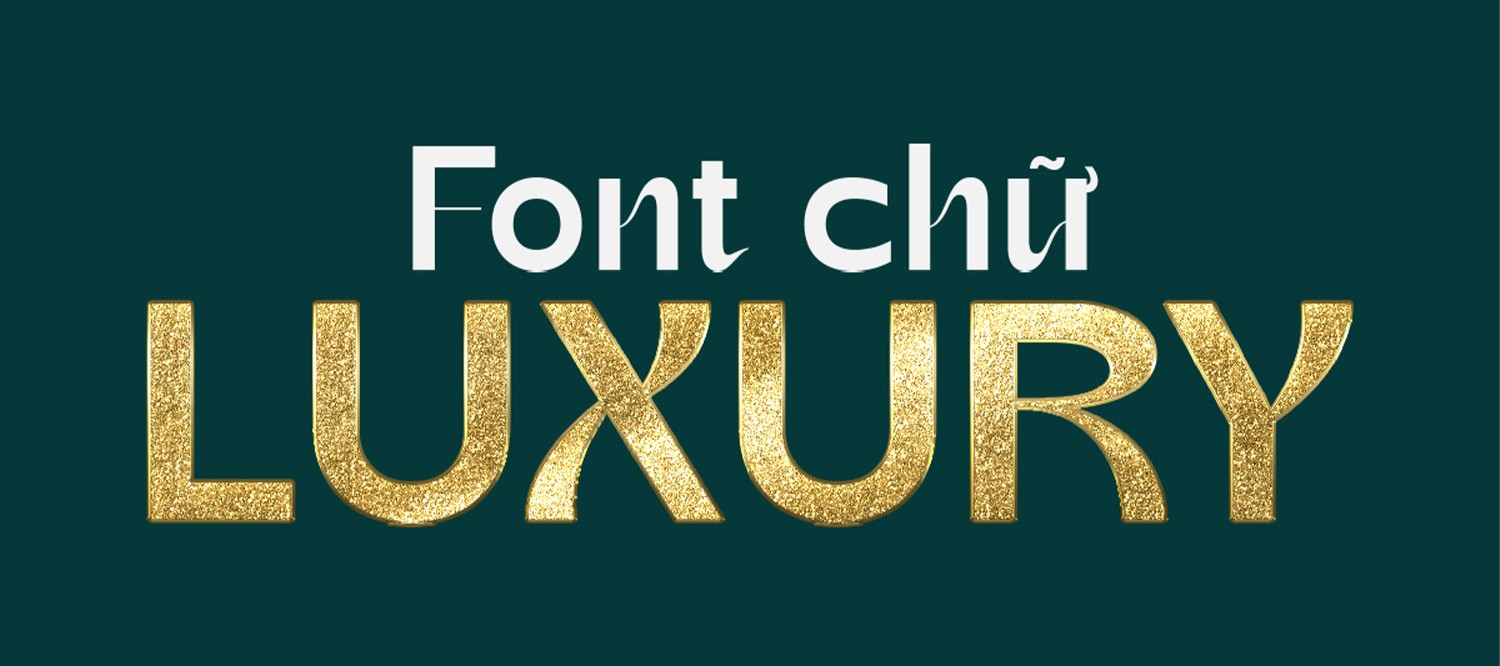
![[Tải Xuống] TOP 15 Font Chữ Luxury Cho Thiết Kế Trở Lên Sang Trọng](https://cdn.s99.vn/blog/fontluxury2.jpg)
Font chữ là yếu tố cực kỳ quan trọng trong thiết kế đồ họa, đặc biệt là với các dự án mang tính chất cao cấp và đẳng cấp.Font chữ luxury, hay còn gọi là font chữ sang trọng, là những kiểu chữ được thiết kế với mục đích tạo ra cảm giác cao cấp, đẳng cấp và tinh tế. Chúng thường được sử dụng trong các thiết kế đòi hỏi sự sang trọng như logo thương hiệu cao cấp, thiệp cưới, ấn phẩm quảng cáo cao cấp, và nhiều hơn nữa.
Font chữ luxury mang đến cảm giác sang trọng, tinh tế và chuyên nghiệp. Đặc trưng bởi đường nét thanh mảnh, tỷ lệ cân đối và chi tiết được thiết kế tỉ mỉ, font luxury thường là serif cổ điển hoặc sans serif hiện đại. Khoảng cách chữ rộng rãi tạo sự thoáng đãng và thanh lịch. Một số ký tự được cách điệu nhẹ nhàng để tạo điểm nhấn riêng biệt. Font luxury phù hợp cho thiết kế logo, bao bì mỹ phẩm, thiệp mời hay thương hiệu cao cấp, giúp nâng tầm hình ảnh và thu hút sự chú ý một cách tinh tế.
Dưới đây là các font chữ luxury sang trọng đã được Việt hóa, phù hợp cho thiết kế thương hiệu cao cấp, thiệp mời, bao bì sản phẩm và nhiều ấn phẩm đòi hỏi sự tinh tế, đẳng cấp. Những font này giúp bạn tạo điểm nhấn ấn tượng và chuyên nghiệp.
Font chữ TH Luxury 7 mang phong cách sang trọng và đậm chất luxury, với các đường nét thanh lịch, mềm mại nhưng vẫn dứt khoát. Thiết kế chữ cái cân đối, phần chân và đỉnh chữ được xử lý tinh tế tạo cảm giác cao cấp, cổ điển. Font phù hợp cho các thiết kế thương hiệu thời trang, mỹ phẩm, bao bì sản phẩm hay thiệp cưới cao cấp. TH Luxury 7 đã được Việt hóa, giúp người dùng dễ dàng ứng dụng trong các ấn phẩm tiếng Việt mà vẫn giữ nguyên vẻ đẹp đẳng cấp vốn có.
Font chữ TH Luxury 5 gây ấn tượng với kiểu dáng hiện đại, thanh thoát và mang đậm tính thẩm mỹ. Các chi tiết uốn cong nhẹ nhàng ở phần chân và đuôi chữ tạo nên cảm giác mềm mại, rất phù hợp cho các thiết kế trong lĩnh vực spa, làm đẹp hay chăm sóc sức khỏe. Phông chữ này mang hơi hướng tối giản nhưng vẫn đủ tinh tế để truyền tải thông điệp về sự thư giãn và cao cấp. TH Luxury 5 là lựa chọn lý tưởng cho thương hiệu cần sự trang nhã và chuyên nghiệp.
Font chữ TH Runsling thuộc nhóm Serif với thiết kế đầy nghệ thuật và sự phá cách trong từng chi tiết. Các nét gạch chân được xử lý uyển chuyển, tạo độ chuyển động nhẹ nhàng, mang đến cảm giác vừa cổ điển vừa hiện đại. Phần đầu chữ được kéo dài hoặc cách điệu một cách tinh tế, giúp font trở nên nổi bật trong các dự án branding, bìa sách hay thiết kế cao cấp. Với phong cách độc đáo và cá tính, TH Runsling là lựa chọn lý tưởng cho những ai yêu thích font Serif mang đậm tính biểu cảm và sáng tạo.
Font chữ TH Vadola gây ấn tượng với kiểu dáng nét mảnh, tinh tế và mang đậm tinh thần luxury hiện đại. Từng ký tự được thiết kế cao ráo, thanh thoát, tạo cảm giác nhẹ nhàng nhưng đầy cuốn hút. Font đặc biệt phù hợp cho các dự án trong lĩnh vực thời trang, làm đẹp hay thiết kế thương hiệu cao cấp, nơi cần sự chỉn chu và sang trọng. Với TH Vadola, mỗi dòng chữ trở nên thanh lịch và đậm chất nghệ thuật, góp phần nâng tầm hình ảnh chuyên nghiệp cho thiết kế.
Font chữ TH Glowen trong ảnh mang hơi thở hiện đại với dáng chữ Serif thanh thoát, được Việt hóa hoàn chỉnh để sử dụng mượt mà trong thiết kế tiếng Việt. Các chi tiết được chăm chút với đường nét mảnh – dày xen kẽ, tạo nên sự tương phản độc đáo, giúp văn bản trở nên nổi bật và thu hút. Font phù hợp với các dự án thiết kế thương hiệu cao cấp, bìa sách, poster nghệ thuật hoặc thời trang. TH Glowen là lựa chọn hoàn hảo cho những ai đang tìm kiếm một kiểu chữ Việt hóa mang phong cách sang trọng, sáng tạo và đầy cá tính.
Font chữ TH Waking sở hữu vẻ đẹp cuốn hút với phong cách thiết kế mang hơi hướng luxury, phù hợp với các thương hiệu trong ngành làm đẹp. Các nét chữ được uốn cong nhẹ nhàng, kết hợp cùng độ dày mảnh linh hoạt tạo cảm giác mềm mại nhưng vẫn giữ được sự sang trọng. Font đã được Việt hóa đầy đủ, hỗ trợ tiếng Việt mượt mà mà không làm mất đi tính thẩm mỹ nguyên bản. Đây là sự lựa chọn lý tưởng để thiết kế logo, bao bì mỹ phẩm hay các ấn phẩm quảng bá cao cấp.
Font chữ TH Ginger sở hữu tỷ lệ chữ cân đối cùng đường nét dứt khoát, mang lại cảm giác mạnh mẽ nhưng không kém phần thanh lịch. Với lối thiết kế mang tính biểu tượng và hiện đại, font này dễ dàng tạo nên dấu ấn cao cấp cho các dự án về thời trang, tạp chí hay nhận diện thương hiệu. Sự sắc sảo trong từng chi tiết giúp TH Ginger vừa giữ được tính truyền thống của serif, vừa tỏa sáng trong các ứng dụng thiết kế đòi hỏi sự khác biệt và đẳng cấp.
Font chữ TH Marlino nổi bật với kiểu thiết kế Serif có chân đầy phá cách và nghệ thuật. Các đầu nét được bo tròn hoặc tạo điểm nhấn bằng những đường cong độc đáo, mang lại vẻ hiện đại nhưng vẫn giữ được tinh thần cổ điển. Sự sáng tạo trong từng chi tiết khiến font trở nên sống động và đậm chất thiết kế, phù hợp với các dự án đòi hỏi sự nổi bật như poster, bìa tạp chí hoặc nhận diện thương hiệu nghệ thuật. TH Marlino không chỉ là một font có chân thông thường, mà là sự hòa quyện giữa phong cách cá tính và sự tinh tế trong từng đường nét.
Font chữ TH Runalto thể hiện sự tinh xảo trong từng đường nét với tỷ lệ hài hòa và các chi tiết uốn lượn độc đáo, tạo nên một diện mạo đầy tính luxury. Dáng chữ mềm mại, thanh mảnh nhưng không kém phần sắc sảo, mang lại cảm giác hiện đại và có chiều sâu thị giác. Đây là lựa chọn lý tưởng cho các dự án thiết kế cần sự sang trọng như logo mỹ phẩm, bao bì cao cấp hoặc bộ nhận diện thương hiệu đẳng cấp. TH Runalto không chỉ là font chữ, mà còn là yếu tố làm nổi bật giá trị và phong cách của sản phẩm.
TH Bevas là một kiểu chữ Serif được thiết kế với phong thái đĩnh đạc, kết hợp giữa sự sắc nét và uyển chuyển trong từng nét kéo. Điểm nhấn nằm ở các ký tự có phần chân mềm mại và cấu trúc thon dài, giúp tổng thể trở nên trang nhã nhưng vẫn mạnh mẽ. Font phù hợp để làm nổi bật các chủ đề mang tính chính xác, cao cấp như đồng hồ, công nghệ hay sản phẩm nam giới.
Font chữ TH Selaris nổi bật với kiểu dáng mềm mại, thanh thoát và đầy tính nghệ thuật. Những nét cong uyển chuyển cùng phần thân chữ kéo dài tạo nên sự duyên dáng rất riêng, phù hợp với các thiết kế trong ngành spa và chăm sóc sắc đẹp. Font không chỉ truyền tải cảm giác thư giãn, nhẹ nhàng mà còn mang theo nét sang trọng tinh tế. Với vẻ đẹp hiện đại pha lẫn cổ điển, TH Selaris là lựa chọn lý tưởng cho các thương hiệu muốn tạo dựng hình ảnh nhẹ nhàng nhưng vẫn chuyên nghiệp và cuốn hút.
TH Charis Moderne mang đến một diện mạo hoàn toàn mới với kiểu dáng độc lạ, tạo điểm nhấn nhờ các chi tiết phá cách táo bạo. Những đường cắt uốn lượn và các khoảng trống không đối xứng khiến từng chữ cái trở nên cuốn hút và khó trộn lẫn. Phong cách thiết kế hiện đại, tinh gọn nhưng vẫn đủ cá tính giúp font này thích hợp cho logo thương hiệu sáng tạo, bìa tạp chí nghệ thuật hoặc các dự án cần yếu tố thị giác mạnh. TH Charis Moderne chính là sự lựa chọn hoàn hảo cho những ai muốn thoát khỏi khuôn mẫu thông thường.
📂 Tải xuống font TH Charis Moderne
TH Grotley là font chữ sans serif thiết kế theo phong cách tối giản và hiện đại, mang lại cảm giác mạnh mẽ và dứt khoát. Các chữ cái viết hoa đều, vuông vức và có độ cân đối cao giúp tăng độ nhận diện và tính thẩm mỹ trong bố cục. Với nhiều tùy chọn độ dày, từ mảnh nhẹ đến đậm nét, font này cực kỳ linh hoạt cho các thiết kế poster, tiêu đề hoặc ấn phẩm thương hiệu. TH Grotley tạo ấn tượng bằng vẻ ngoài chỉnh chu, tinh gọn, phù hợp với những dự án cần thể hiện sự chuyên nghiệp và nghiêm túc nhưng vẫn mang nét trẻ trung, hiện đại.
TH Maginia sở hữu cấu trúc chữ thanh mảnh kết hợp với các đường nét uốn lượn duyên dáng, tạo nên cảm giác vừa nhẹ nhàng vừa đầy tinh tế. Sự chắt lọc trong từng chi tiết mang lại vẻ đẹp chuẩn mực, rất thích hợp cho các thiết kế mang định hướng cao cấp như thương hiệu làm đẹp, thời trang hay tiệc cưới. Font còn gây ấn tượng với những yếu tố trang trí nhẹ, giúp bố cục trở nên nổi bật nhưng không hề phô trương. Với TH Maginia, sự sang trọng được thể hiện một cách tinh tế qua từng con chữ.
Bước 1: Tải file font chữ về và giải nén, nhấn chuột phải vào file chọn Extract Here lưu ý máy bạn phải cài các phần mềm giải nén file nhé
Bước 2: bạn mở lên chọn với font chữ bạn muốn cài rồi chọn Install, nếu muốn cài hết font chữ thì ấn ctrl + A rồi chọn install for all users
Ngoài ra bạn cũng có thể cài đặt theo cách copy và paste trực tiếp vào trong thư mục Font của máy tính.
Bước 1: Bạn chọn tất cả các font chữ muốn cài đặt và chuột phải chọn Copy hoặc ấn phím tắt Ctrl + C để copy các font chữ
Bước 2: Bạn vào thư mục theo đường dẫn C:\Windows\Fonts trong My Computer và nhấn Ctrl + V để paste các font chữ. Như vậy là đã hoàn thành cài đặt các font chữ vào máy tính.
Font chữ luxury không chỉ đơn thuần là yếu tố thẩm mỹ mà còn là cách để thể hiện đẳng cấp và sự chuyên nghiệp trong thiết kế. Việc sử dụng font chữ Luxury Việt Hóa không chỉ giúp bạn tạo ra những thiết kế đẹp mắt mà còn góp phần nâng cao giá trị thương hiệu của bạn. Hãy lựa chọn những font chữ phù hợp để tạo nên những sản phẩm độc đáo và ấn tượng. Hãy khám phá và sử dụng các font chữ luxury việt hóa để tạo nên những thiết kế nổi bật và ấn tượng cho dự án của bạn, giúp nâng tầm thẩm mỹ và giá trị thương hiệu một cách tốt nhất..